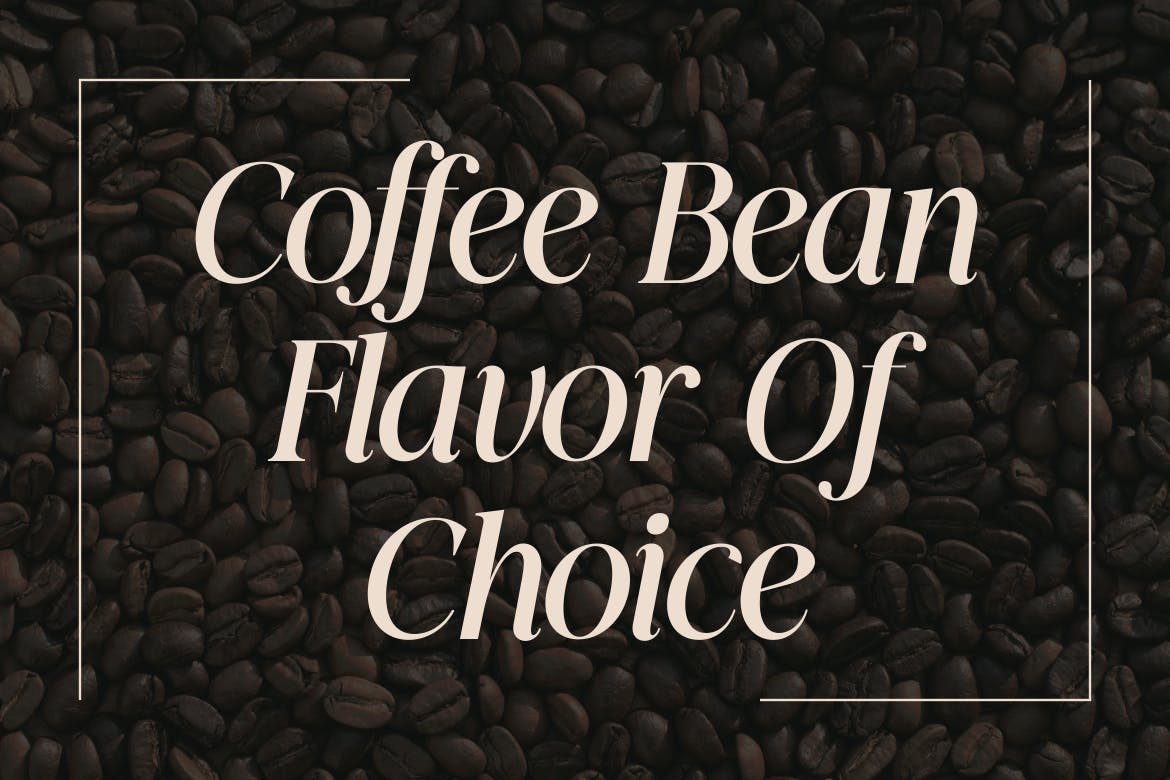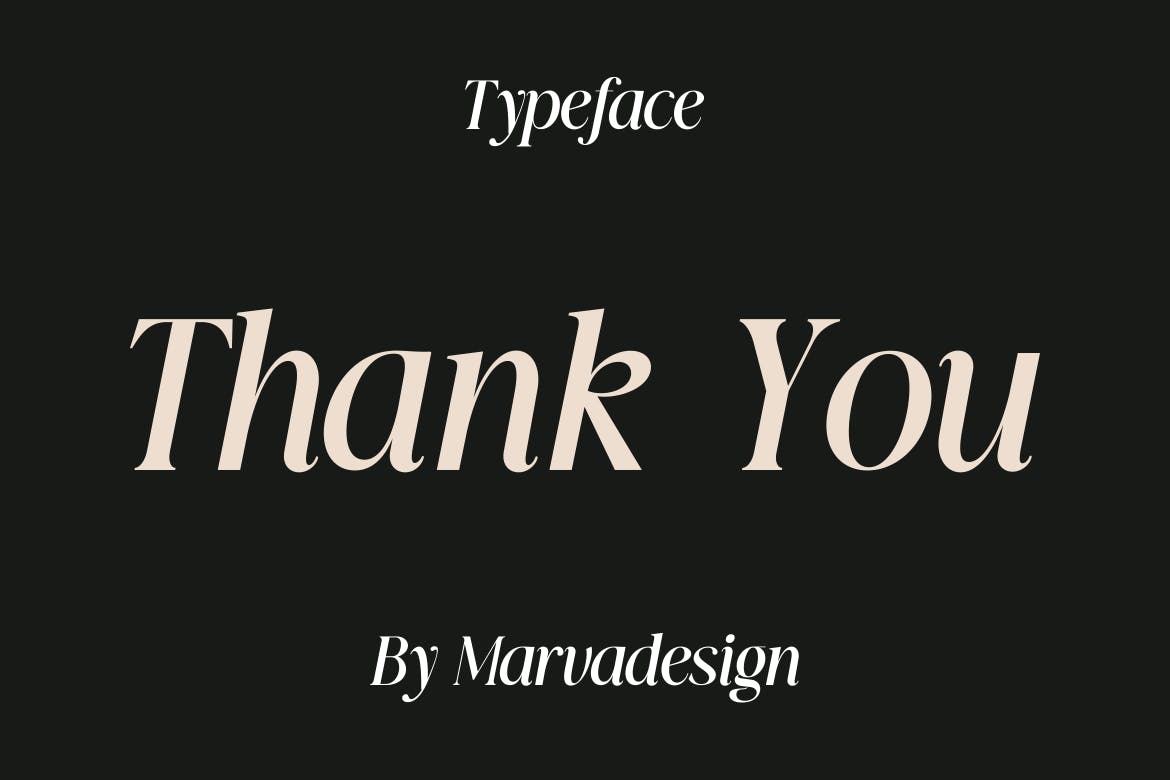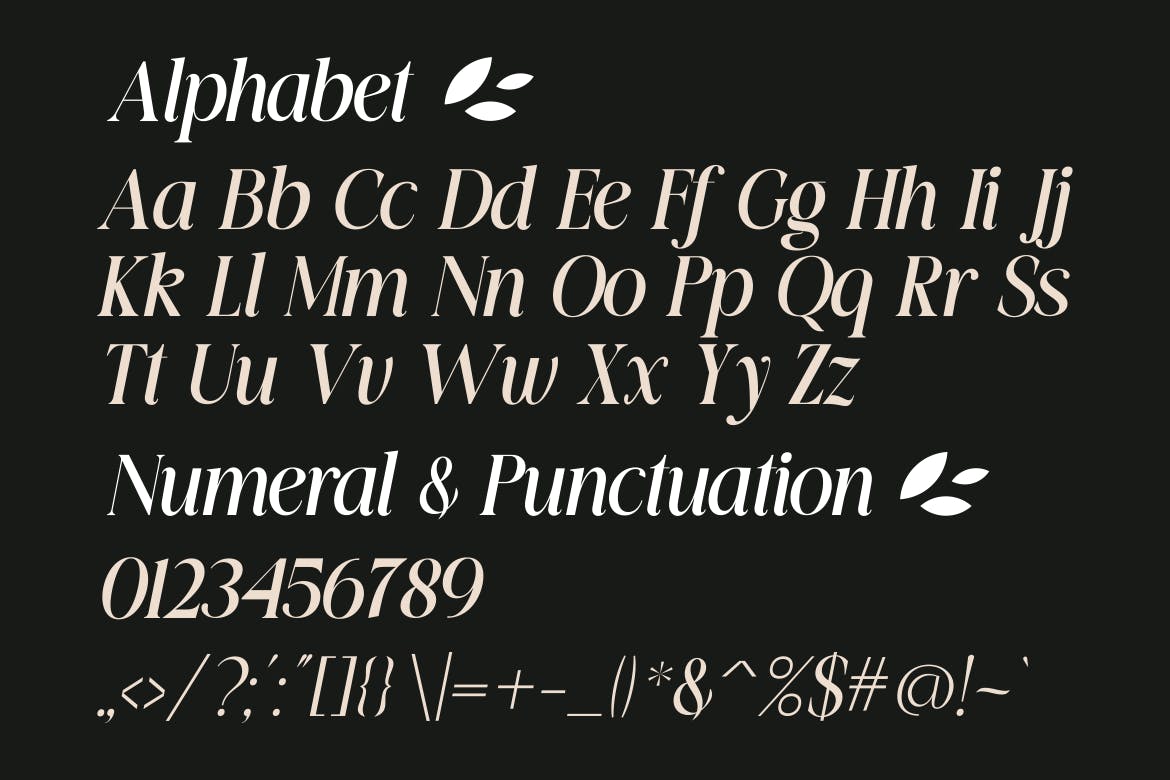
دانلود فونت مدرن Coffins برای طراحی
Coffins A Modern Serif Font
فونت مدرن Coffins مناسب برای پروژه‌های طراحی و برندینگ.
معرفی محصول جدید ما فونت Coffins - فونت مدرن، یک فونت نمایش bold و اصیل است. این فونت برای هر پروژه برندینگ مانند لوگو، چاپ تیشرت، محصولات و بسیاری موارد دیگر مناسب است و در طیف وسیعی از زمینه‌ها عالی عمل می‌کند.
• حروف بزرگ
• حروف کوچک